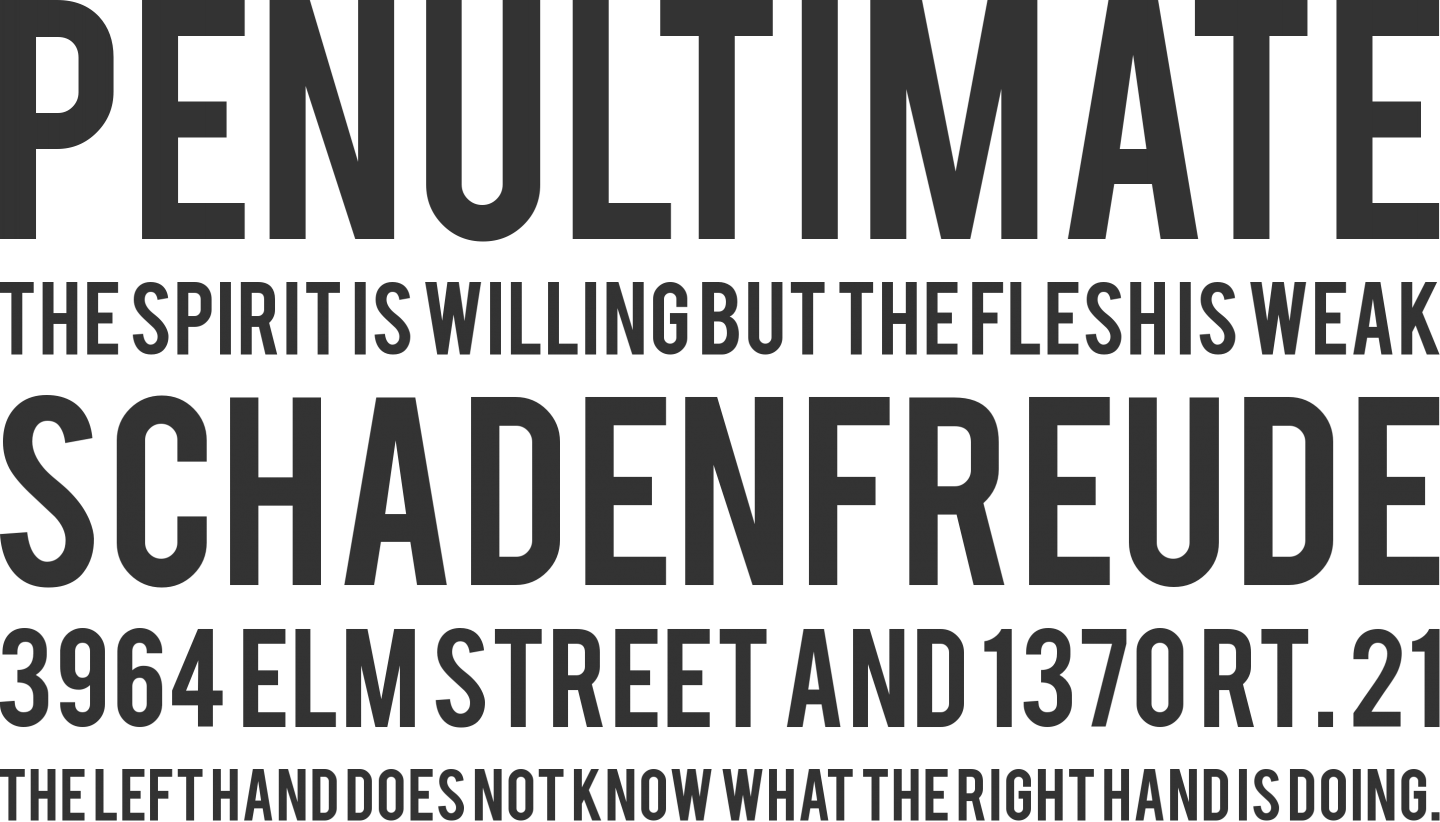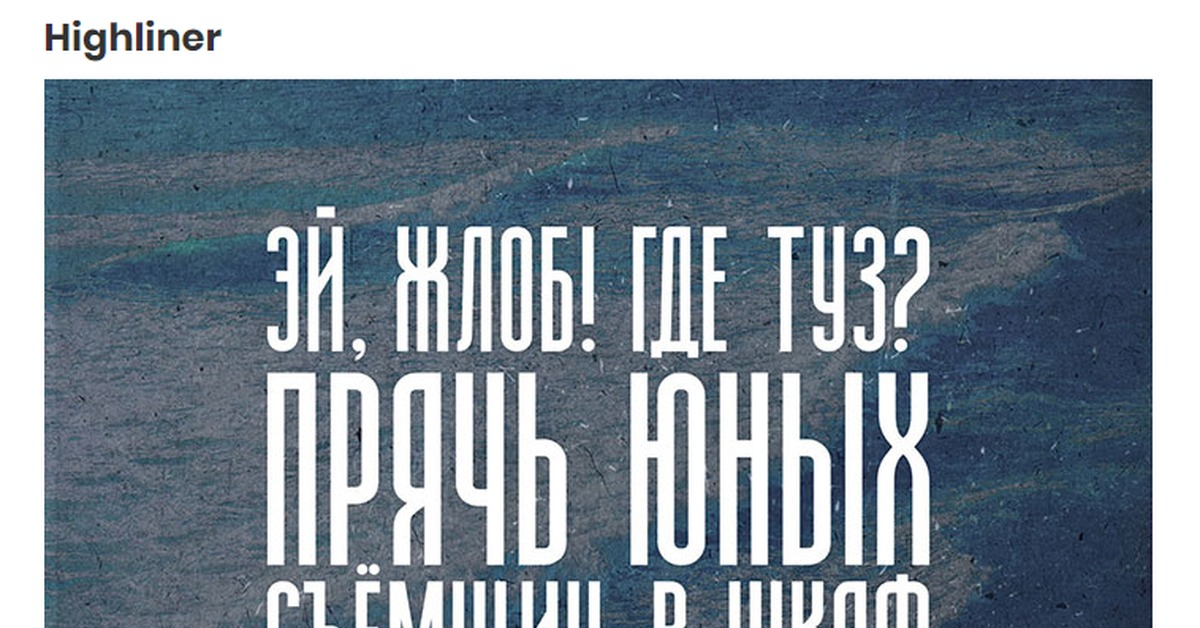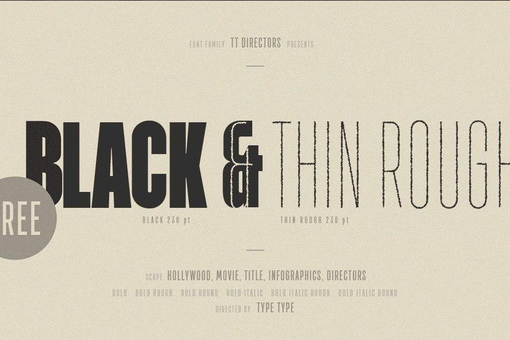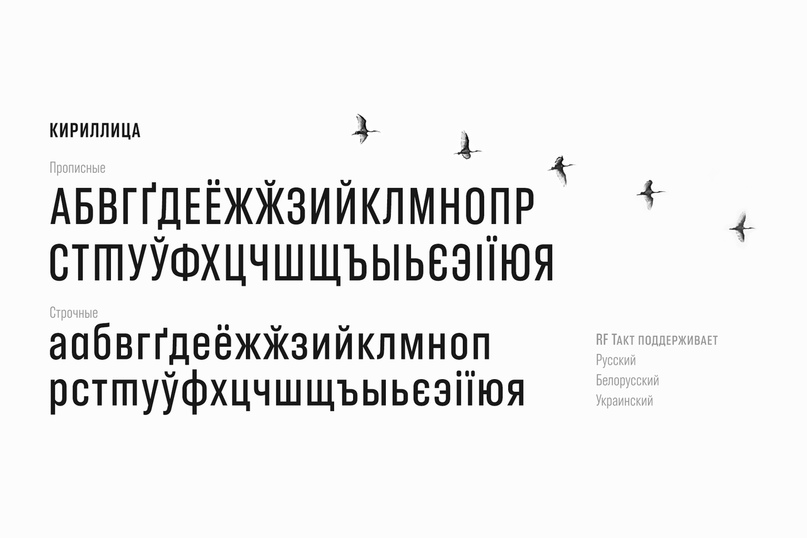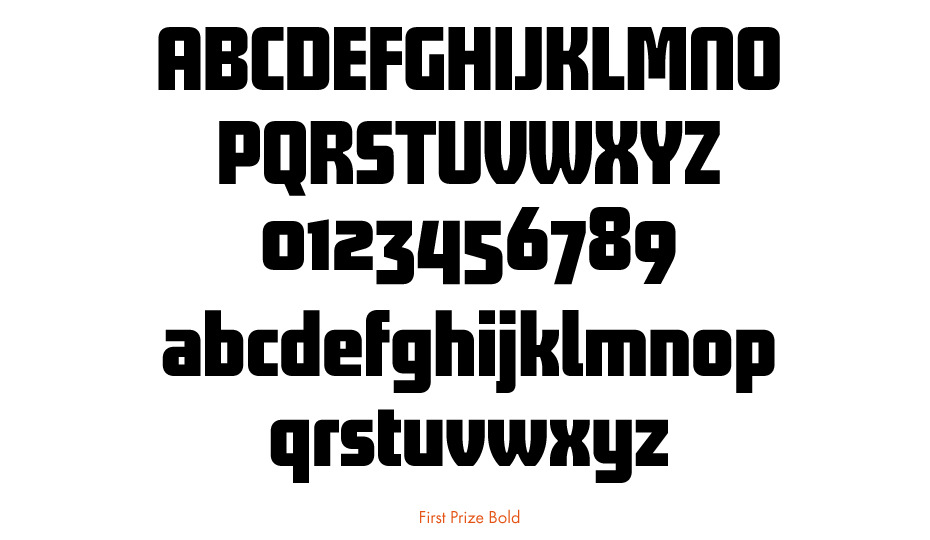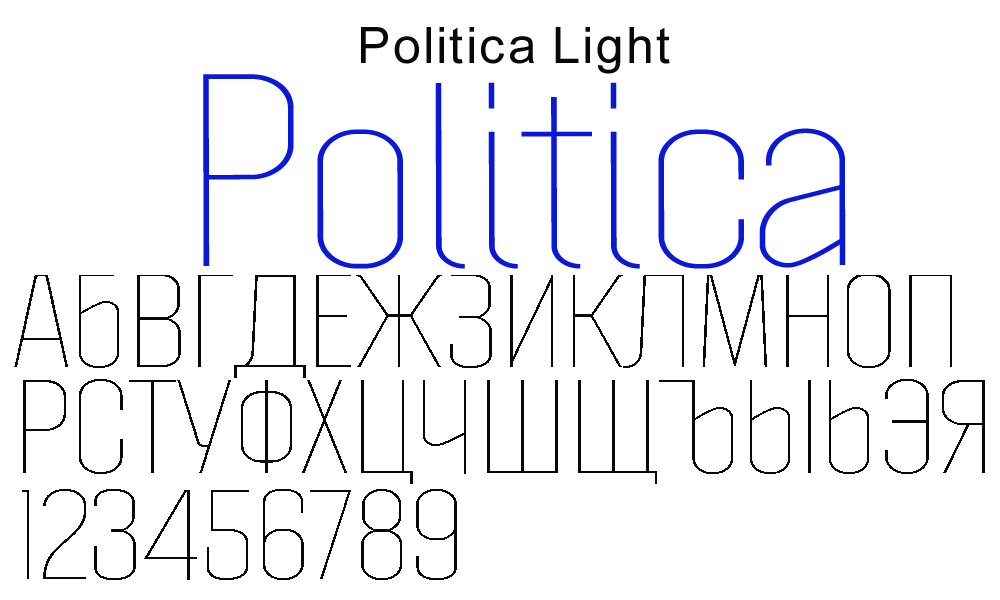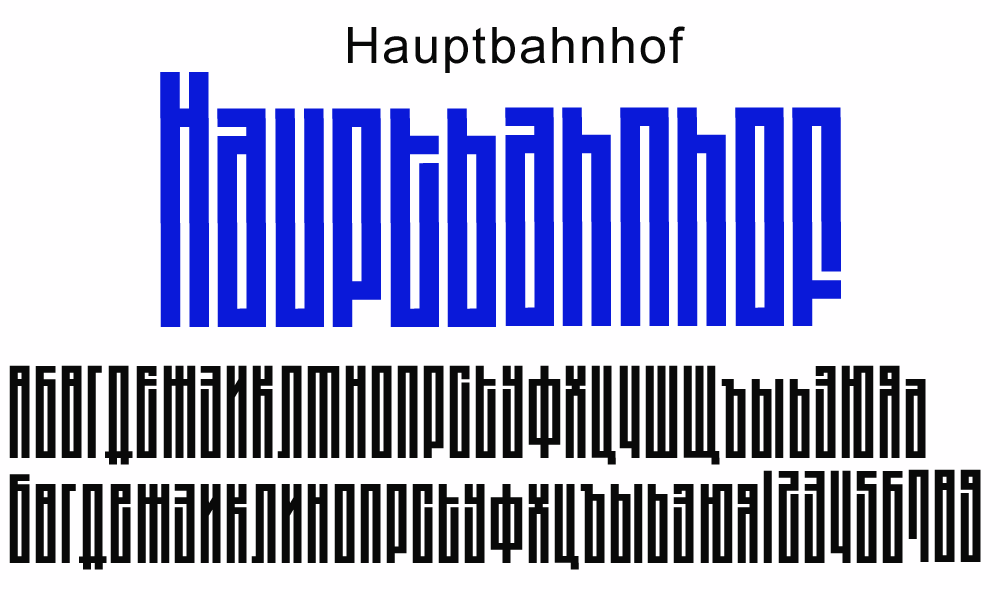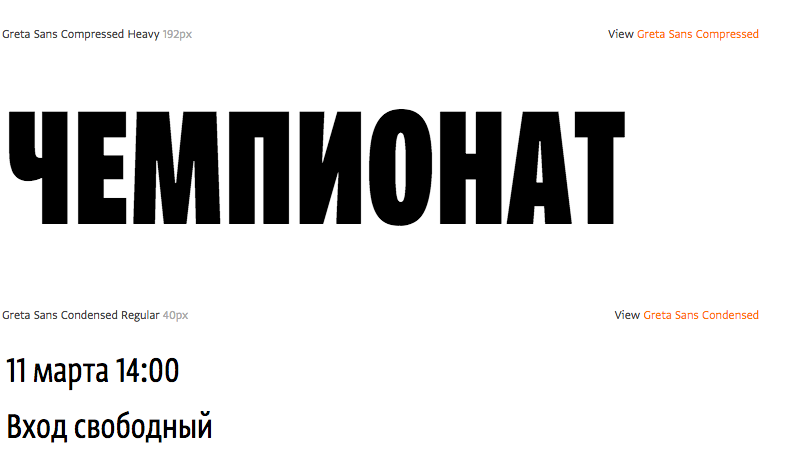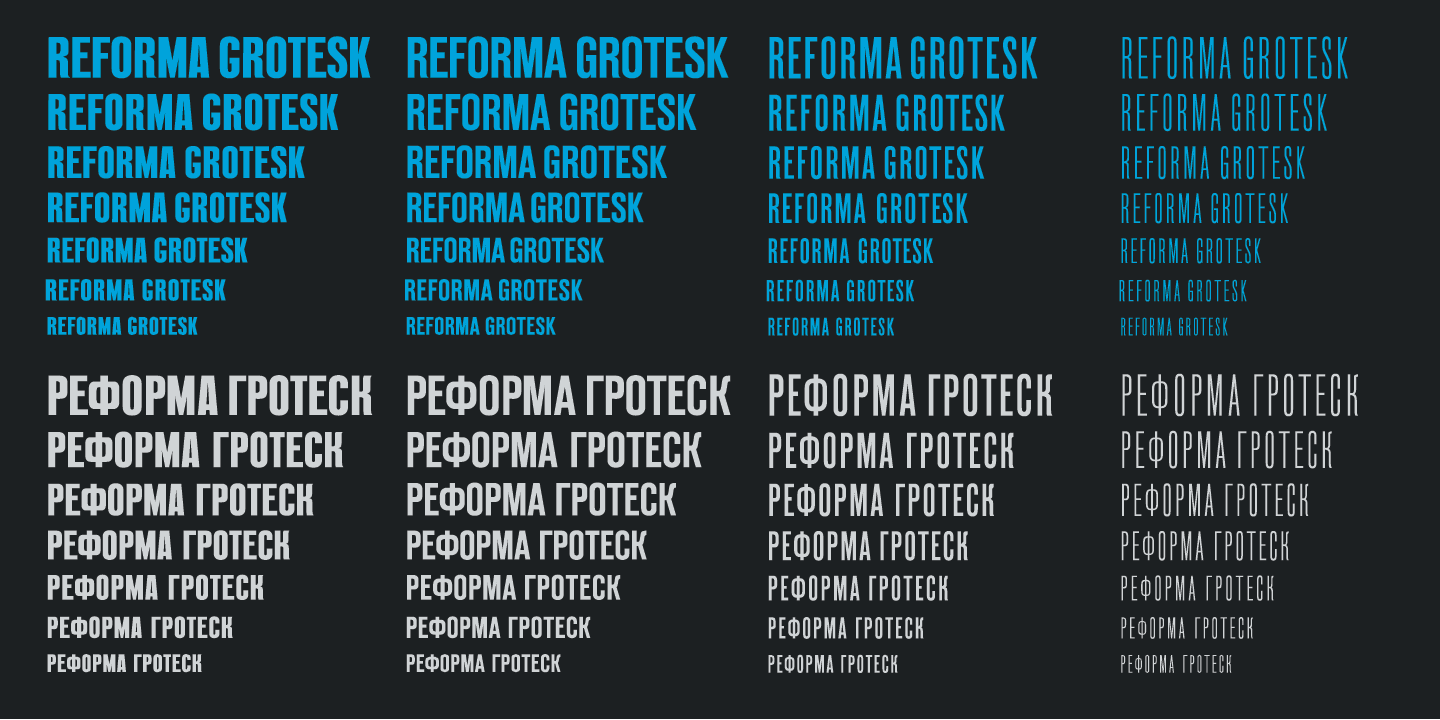
Узкие шрифты кириллица: ТОП 30 Узник и высоких шрифтов 2020 года cкачать Ⓐ Shriftkrasivo.ru
ТОП 30 Узник и высоких шрифтов 2020 года cкачать Ⓐ Shriftkrasivo.ru
Подборка узких и высоких шрифтов
Вопреки распространенному мнению, сжатые и узкие шрифты не делают ваш текст тесным или переполненным. Вам просто нужно знать подходящее время и место для использования шрифта. Конденсированные шрифты широко используются в наши дни для заголовков и отображения смелых сообщений, и при развертывании в нужном месте они могут дать потрясающий эффект!
Сокращенный или узкий шрифт — это шрифт, в котором есть символы с узкой шириной, но он также относится и к шрифтам с более высоким дизайном символов. Сокращенные шрифты также имеют гораздо более узкое пространство между символами, чем обычный шрифт.
Devant Pro
Devant Pro — это современный сжатый узкий шрифт, который отличается большим и смелым дизайном, что делает его идеальным для заголовков сайтов, плакатов, баннеров, листовок и многого другого.
Шрифт определенно пригодится при разработке смелых названий для цифровых и печатных дизайнов.
Config
Config — это семейство сжатых шрифтов с высокопрофессиональным дизайном без засечек. Он включает в себя 20 различных шрифтов, которые вы можете использовать с различными типами дизайнов, как в качестве заголовка, так и шрифта абзаца.
Edingu
Edingu — это элегантный сжатый шрифт с современным дизайном, который идеально подходит для профессионального дизайна, роскоши и брендинга. Шрифт доступен в 3 различных стилях, включая обычный, округленный и курсив.
CONQUEST
Conquest — это жирный шрифт с засечками и слегка сжатым дизайном. Он наиболее подходит для создания заголовков и заголовков, связанных со спортивными и развлекательными брендами. Шрифт также доступен в вариантах без засечек и с засечками.
Story Telling – Fun Condensed Font
Этот забавный и причудливый сжатый шрифт — отличный выбор для создания плакатов, поздравительных открыток, обложек книг и многого другого, связанных с детьми всех возрастов.
Efesto
Efesto — еще один бесплатный шрифт с высоким и узким дизайном. Этот шрифт также совершенно бесплатно использовать с вашими коммерческими и клиентскими проектами. Он включает в себя как обычный, так и курсивный стили шрифта.
Forever Freedom
Это современное семейство шрифтов имеет несколько шрифтов с разным весом и стилями. Включая курсив и наброски. Все шрифты также имеют узкий, сжатый дизайн.
ARGON
Argon — это идеальный шрифт, который вы можете использовать для разработки логотипов и названий для современного бизнеса. Этот шрифт содержит набор уникальных узких букв, в отличие от любого другого шрифта в нашем списке. Это также входит в 4 различных веса.
Norfolk
Эта элегантная пара шрифтов включает в себя как узкий шрифт без засечек, так и шрифт с полужирным шрифтом. Два из которых прекрасно сочетаются друг с другом.
Вы можете использовать оба шрифта для оформления заголовков или даже абзацев.
Due Credit
Жирный и узкий шрифт без засечек для оформления заголовков и заголовков. Этот шрифт наиболее подходит для постеров, заголовков веб-сайтов и дизайна заголовков. Он поставляется в нескольких весах и включает как заглавные, так и строчные буквы.
Parkia
Parkia — это семейство сжатых шрифтов, которые включают шрифты разных стилей и веса шрифтов. Вы можете использовать этот шрифт с различными типами профессиональных и творческих проектов, а также с дизайном для печати.
Las Valles
Этот элегантный и сжатый шрифт является отличным выбором для разработки логотипов, заголовков веб-сайтов и флаеров для роскошных и высококлассных брендов. Шрифт включает в себя все заглавные буквы вместе с пунктуацией и цифрами.
Sprout
Sprout отличается высоким и узким дизайном, который делает его отличным шрифтом для создания всех видов дизайнов, включая поздравительные открытки, заголовки веб-сайтов, плакаты, посты в социальных сетях и многое другое.
Tallios
Шрифт Tallios отличается узким дизайном и стильными закругленными краями. Он наиболее подходит для создания постов в социальных сетях, цитат, постеров и дизайнов футболок. Шрифт включает как прописные, так и строчные буквы.
GATSBY
Gatsby — это элегантный сжатый шрифт, который вы можете использовать для всех видов профессионального, делового и брендингового дизайна. Кажется, он особенно подходит для брендов класса люкс и модных дизайнерских проектов.
Calcio
Шрифт Calcio отличается очень сжатым дизайном, который придает ему более узкий вид. Шрифт лучше всего подходит для создания заголовков, заголовков и постеров. Он включает как прописные, так и строчные буквы и символы.
Nomads
Nomads — это сжатый шрифт со старинным дизайном. Лучше всего подходит для создания значков, этикеток и логотипов для компаний и брендов в винтажной тематике. Шрифт поставляется в обычном, закругленном и винтажном стилях.
Chillvornia
Шрифт Chillvornia поставляется с уникальным дизайном ручной работы с декоративными буквами. Этот шрифт идеально подходит для создания значков, постеров, заголовков и заголовков в стиле винтаж.